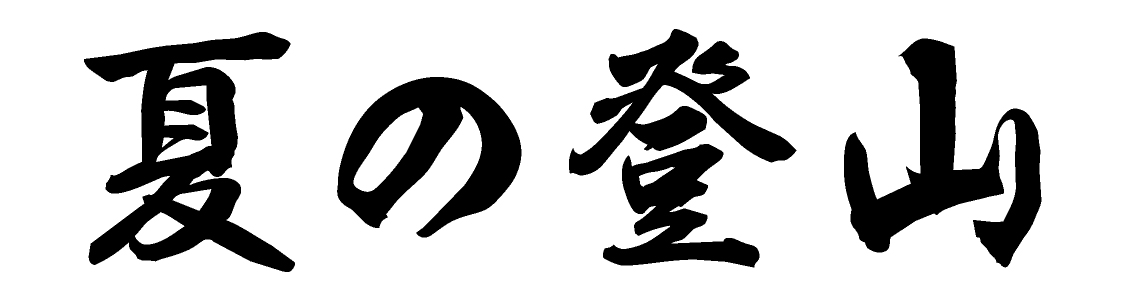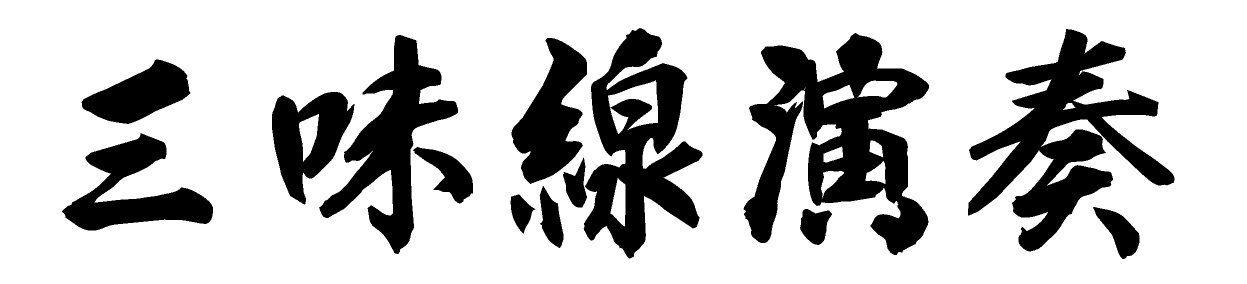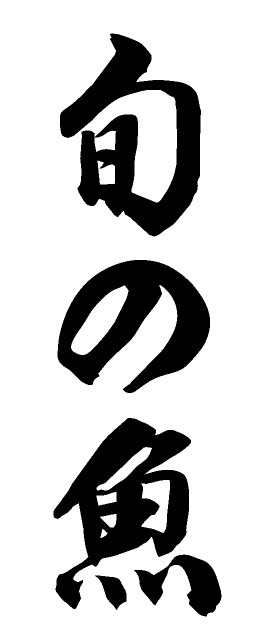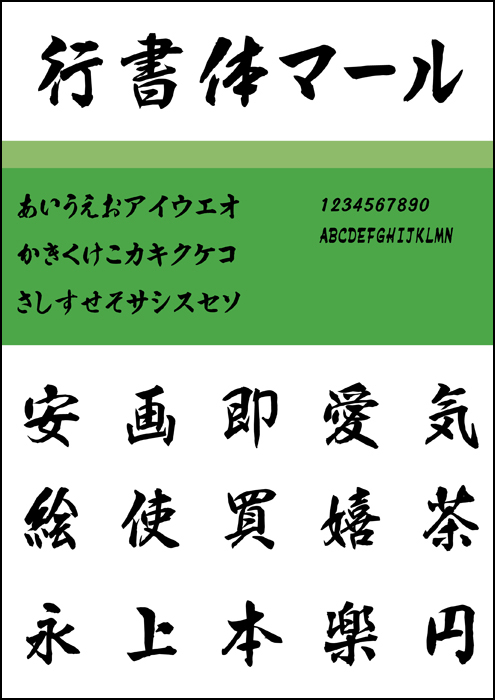
行書体マール (ダウンロード版)
【書:川原石光】
弊社書籍『ディスプレイ書体集 行書体字典』(川原石光 著)をフォント化したものです。実用的な「平明な行書体が欲しい」という声にお応えしました。流れるような線の美しさ、力強い筆勢の逞しさなどは持ちつつも、書きやすく、バランスのとれた文字を収録しています。ポスターやチラシ、お品書き、同人誌の表紙など、あらゆる場面で大活躍のフォントです。フォントフォーマットはTrueTypeです。印刷物への使用など一般的な商業利用は追加料金なしで可能です。詳細については、上記リンク「使用許諾範囲」を、ご購入前に必ずご確認ください。